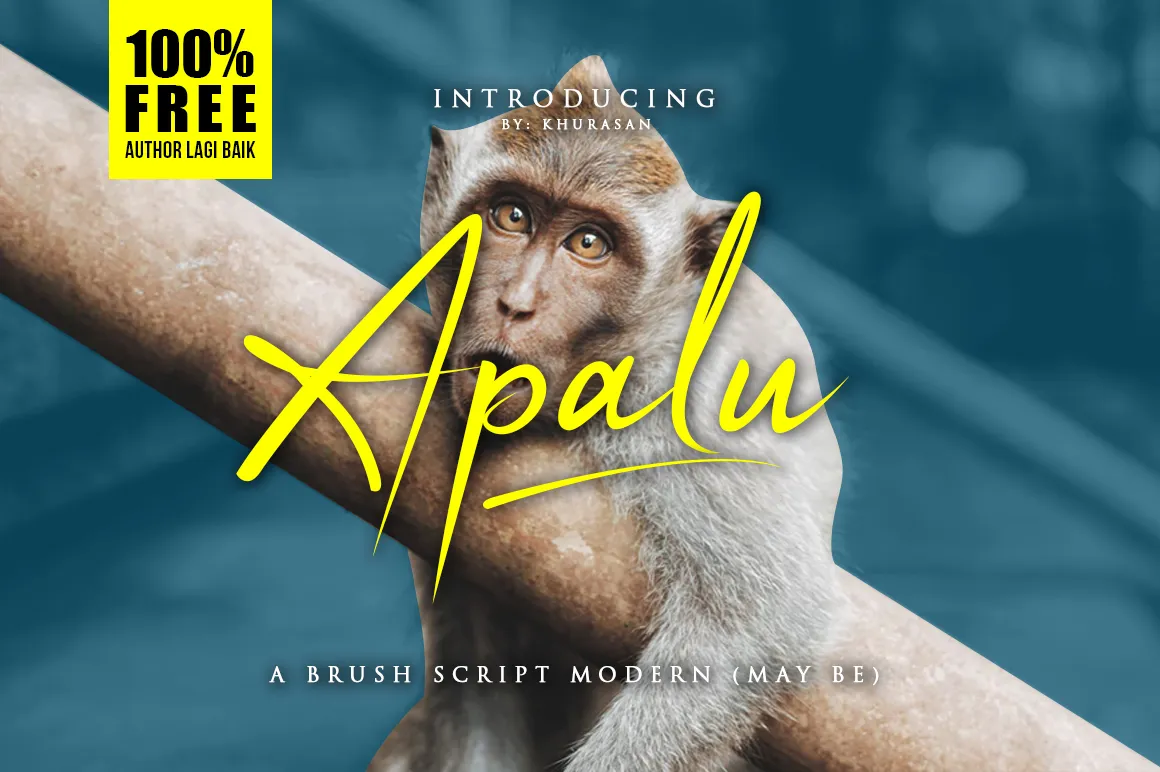
Agradecemos pelo seu interesse. Oferecemos para você uma paleta especial de fontes gratuitas neste pacote. Apalu Script Font é a escolha perfeita para seus projetos, com sua graça moderna e feminina. Desenvolvida por Syaf rizal, o designer Hamilton introduz-nos à Apalu Script Font. Esta fonte foi criada com cuidado e possui um estilo que se encaixa perfeitamente em design colorido, logotipos casual, apresentações, revistas, sinalizações, panfletos, gráficos de citação ou qualquer outro projeto onde você deseja dar uma pitada especial. Faça o download agora e prepare-se para um momento divertido e criativo!